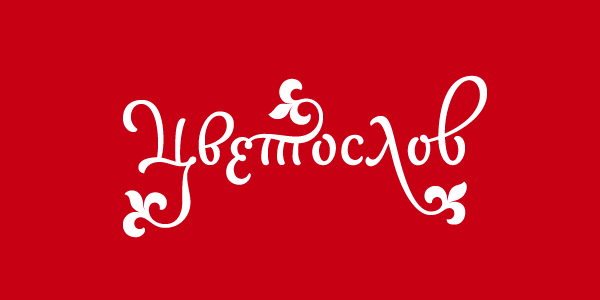
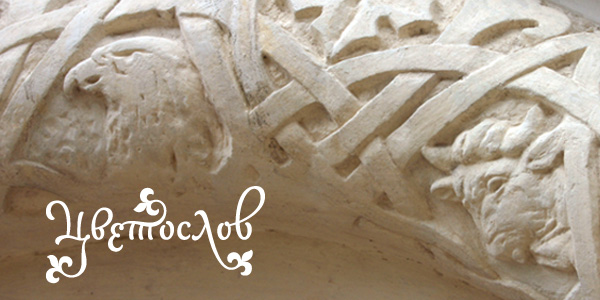
Цветослов
Логотип для издательского проекта «Литургическое наследие Православной Церкви».
Цветослов — дословный перевод с греческого «анфологиона» (или антологии). Так называется «Праздничная Минея». Основными задачами проекта являются собирание и сохранение литургического наследия Православной Церкви.
В основу логотипа легли элементы каллиграфической скорописи и цветочные орнаменты XVII века.